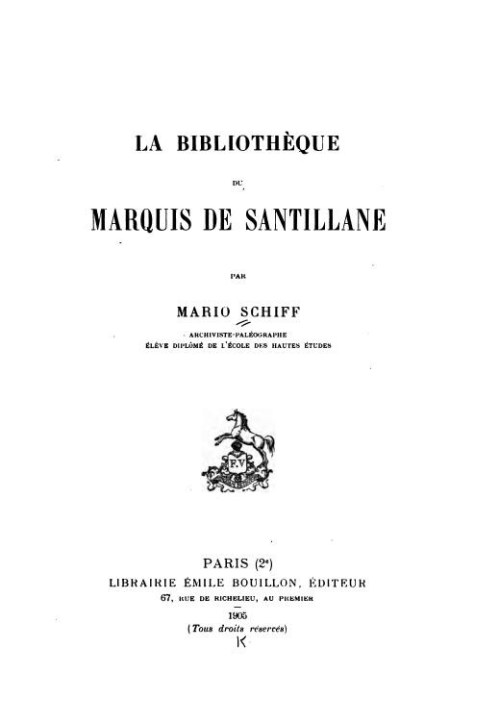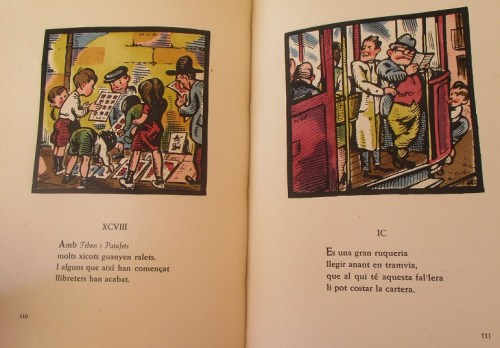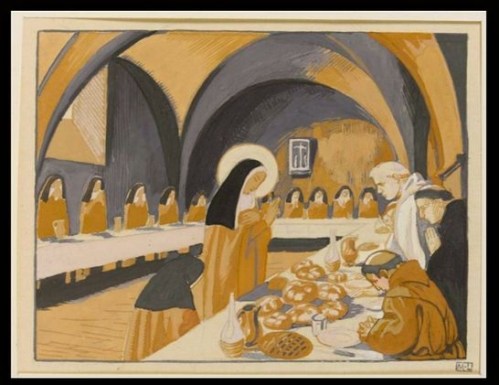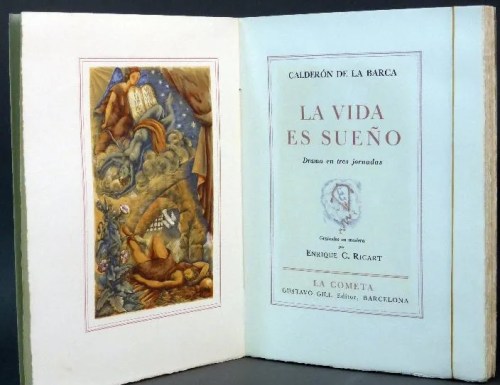
“Un llibre pot arribar a ser una obra d’art i per aconseguir obres d’art no hi ha fórmules que valguin. Amb tots els elements estudiats es pot fer un llibre bell o es pot fallar. L’excel·lència de les parts no condueix forçosament a la perfecció del tot. Els elements que formen un llibre han de ser manejats per un artista que tingui una idea de conjunt. Això no vol dir que l’il·lustrador tingui forçosament de treballar al dictat, però sí que ha d’obeir a unes directrius encaminades a l’harmonia total. El caràcter i la personalitat d’un llibre són les característiques més difícils d’aconseguir i no es poden deixar a l’atzar. Si cada llibre és diferent pel que fa al text que conté, la materialitat del mateix ha de tenir així mateix unes peculiaritats pròpies. No abonem l’originalitat com a sistema o com a meta, sinó com a resultant lògica de les coses.
Un llibre d’alta bibliofília no solament és un text, unes il·lustracions, o un magnífic paper, sinó tots aquests elements alhora, i una cosa única i alhora diferent.
Marca tipogràfica de Ludwig Elzevir ( Leiden, 1595).
Davant d’aquestes consideracions hem assistit a l’imperi d’altres molt diferents i que sovint han estat les següents:
1ª Un llibre de bibliòfil ha de ser un llibre car.
2ª Ha de ser de tiratge limitat.
3a Ha d’estar il·lustrat.
4a Ha d’estar imprès sobre paper de fil.
…/…
Per a més d’un esperit simplista, la sola possessió d’una d’aquestes característiques ja justifica el qualificatiu de llibre per bibliòfil.
Efectivament, un llibre per a bibliòfil pot resultar car, perquè les coses ben fetes necessiten temps per fer-les i el temps s’ha de pagar, com igualment és costós el paper bo i cal pagar també l’il·lustrador. Però no sempre els llibres més cars són els millors i amb elements senzills es poden fer grans coses. L’harmonia i l’equilibri, la direcció encertada no tenen res a veure amb les despeses materials. Edicions atapeïdes amb il·lustracions i coloraines poden ser un desastre.
Un llibre pot ser bell amb poques il·lustracions i fins i tot sense cap, cal veure pàgines impreses pels grans artistes impressors – hem dit grans artistes impressors, no grans impressors -, per comprendre tota la bellesa que pot resultar del simple joc de les lletres negres sobre el paper. Bodoni, els Elzevir, Ibarra, ens han llegat pàgines de suprema harmonia, concebudes amb un esperit gairebé podríem dir arquitectònic. La il·lustració és bona i desitjable com a element de riquesa i quan està en funció de la tipografia..
“ –Y a ese Gustavo Gili, editor, a quien no tengo el gusto de conocer ni en sueños; le ha cogido muy en serio; porque, además de esta Semana Santa, anuncia, bajo el signo de “La Cometa”, otras varias obras de bibliofilia lujosa – El sombrero de tres picos, con aguafuertes de Javier Nogués; El alcalde de Zalamea, con litografías de José de Togores; La vida es sueño, con hojas de Enrique Ricart; las Elegías, de Eduardo Marquina, con puntas secas debidas a una dama artista, Laura Albéniz de Moya, hija del gran compositor-; una serie de libros, en fin, en los cuales el editor va a perder todo el dinero que le cuesten.
El Alcalde de Zalamea
-¿ Cree usted? Le advierto que ese hombre lleva ya empleada en libros – en ejemplares comprados para su biblioteca particular – una verdadera fortuna.
-¡Qué barbaridad! De tanto tratar en libros habrá acabado como don Quijote, por ser víctima de ellos.
– Hay que reconocer, en todo caso, que si esto es locura, es la más noble locura para un editor.
– Y ahora quiere contagiar a los menos lectores ¿ no es eso?
– Por ahí anda, realmente. Se le ha metido en la cabeza que lo que se hace en los países más cultos de Europa, y especialmente en Francia, no hay razón ninguna para que no se haga aquí.
– Mucha ambición es esa.
– Ciertamente. ¡Cualquiera se pone a fabricar y vender libros-joyas, en un país en donde los primeros escritores no tiran ni venden más de dos mil ejemplares baratos, de los de a cinco pesetas!… Vamos a ver; usted misma, ¡qué regalo prefiere? ¿ El Renard de antaño o el libro de hogaño?
– El libro me gusta muchísimo, pero la piel…
– Sea usted sincera.
– Pues la piel, no sé; cuando menos podrá durarme varias temporadas.
-¿ Nada más?
– ¿ Y le parece poco?
– Pues cuando del Renard no le quede a usted ni un vago ni apolillado recuerdo, ese ejemplar de Semana Santa, imperecedero como el mármol y el bronce, habrá alcanzado por su íntima y misteriosa virtud, sin moverse de la vitrina o la biblioteca donde usted lo guarde, por lo menos el triple del valor que ahora tiene.
-¿ Es posible?
– Seguro. Tal es la peregrina y mágica vitalidad del libro-joya. No basta el dinero para saber apreciar el verdadero talismán, y distinguir el libro que es una obra de arte, o una obra rara, del que sólo refleja un esnobismo pasajero. Es necesario, además, tener el gusto y la inteligencia de la bibliofilia. Pero, con ellos, no hay valor en el mundo – ni petróleos, ni minas de carbón, ni fuerzas eléctricas, ni algodones, ni azúcares – que haya alcanzado, en los últimos veinte años, un alza comparable a la obtenida por algunos libros que al salir a la luz sólo llamaron la atención de “cuatro locos” y de “cuatro gatos”
– ¿ Y cómo habríamos podido ser uno de ellos?
– Usted y yo, querida amiga, habríamos podido comprar, por ejemplo, no hace muchos años, un ejemplar de Las florecillas de San Francisco, ilustradas por Mauricio Denis. Habríamos pagado por ellas, en el peor de los casos, unos 400 francos. Y a estas horas, siempre que nos diese la gana, podríamos venderlas por 20.000. Dígame si usted, su marido o alguna de sus amistades posee un capital, una finca o un valor cualquiera que pueda compararse con ese libro fabuloso.
Art. 5. El verdadero bibliófilo es aquel que exige de un libro calidad de texto, belleza de ilustraciones, excelencia artística y técnica en su presentación.
Art. 6. El verdadero bibliófilo posee una biblioteca que conserva su valor constante y constituye para él una verdadera fuente de goce espiritual. Él solamente tiene derecho al título de Bibliófilo moderno’.
Gravat en el llibre de Robert.